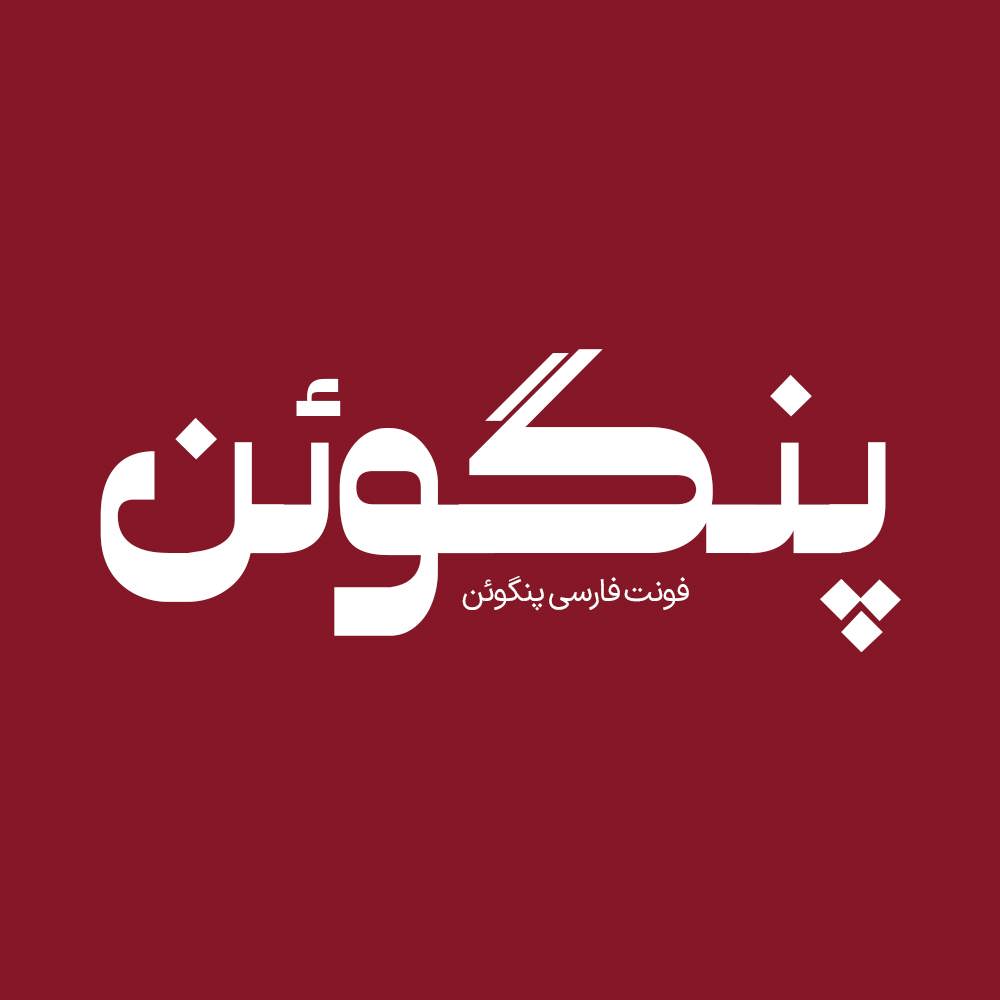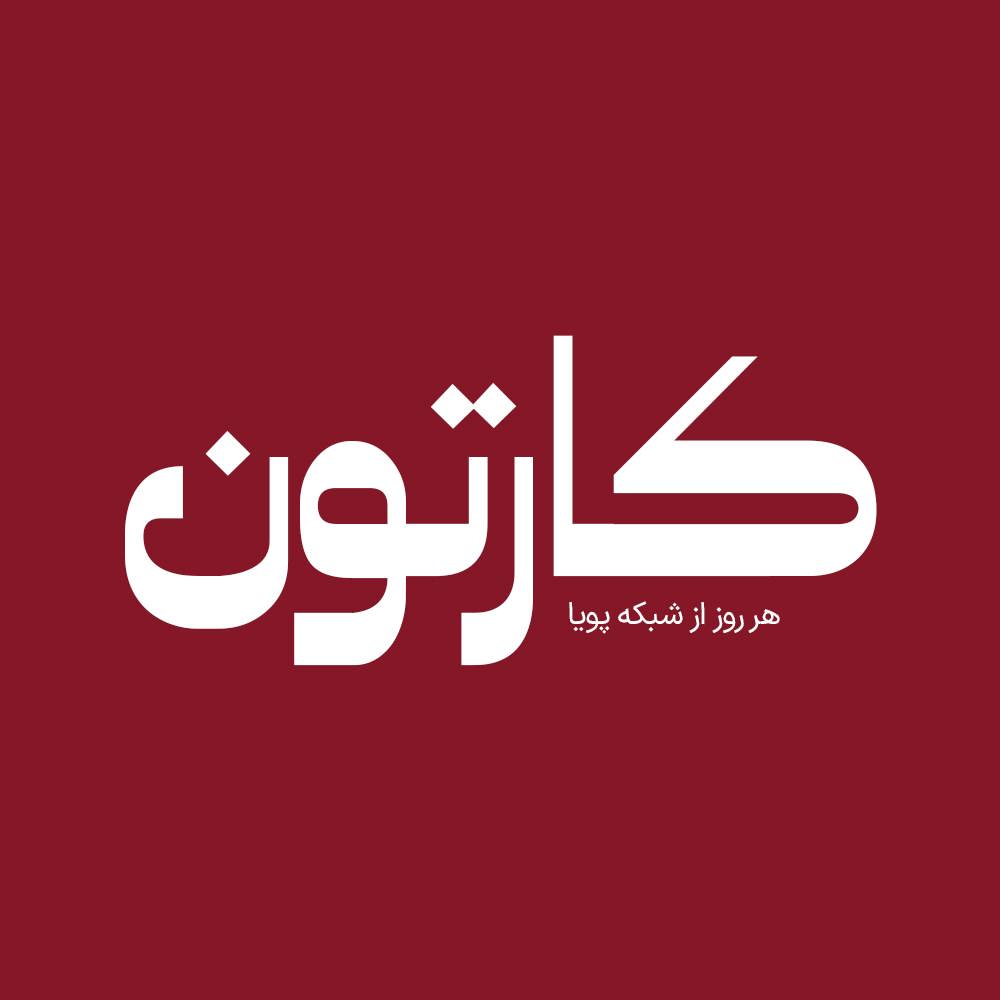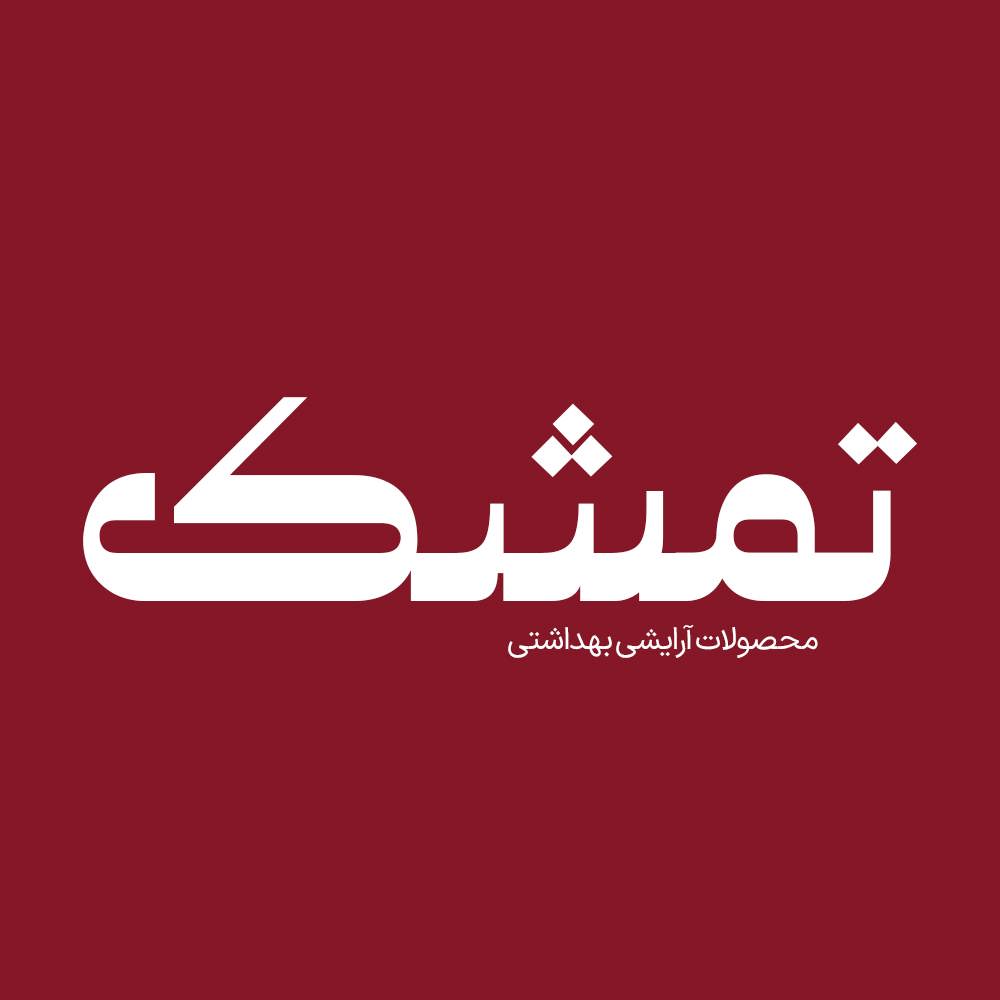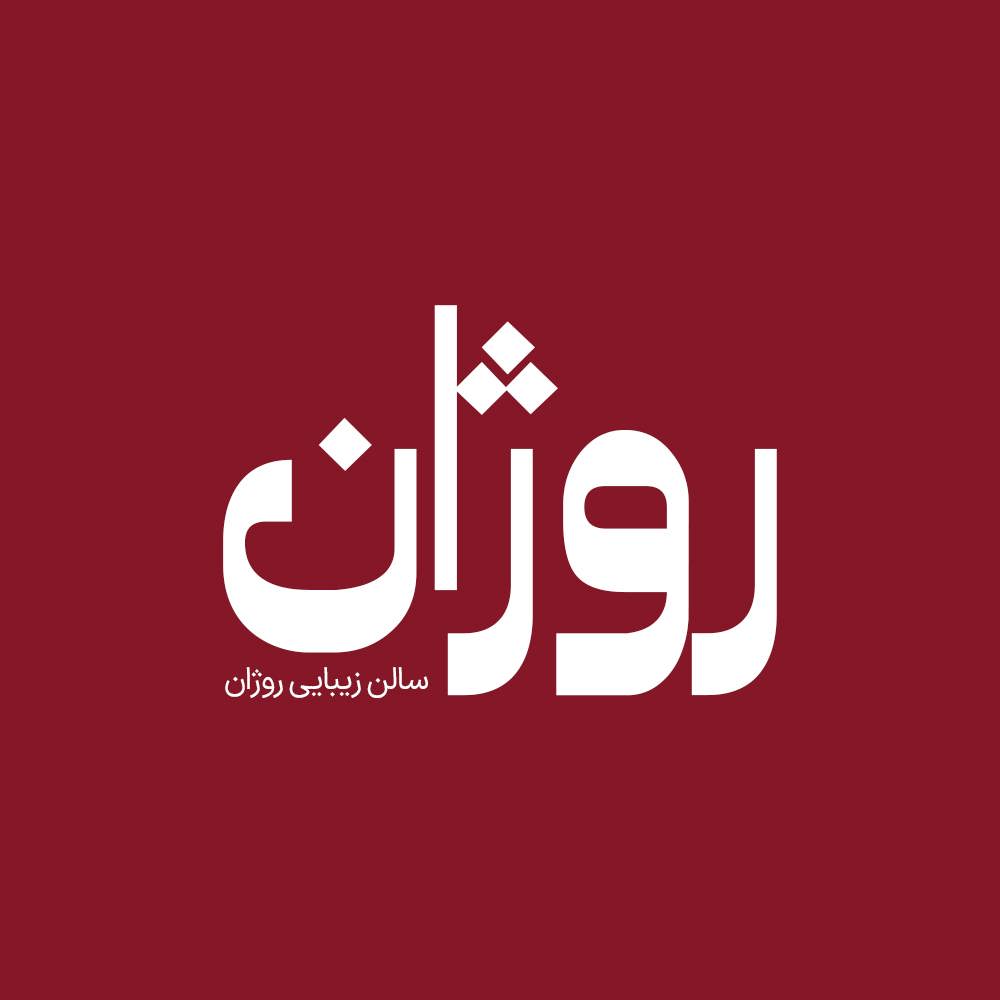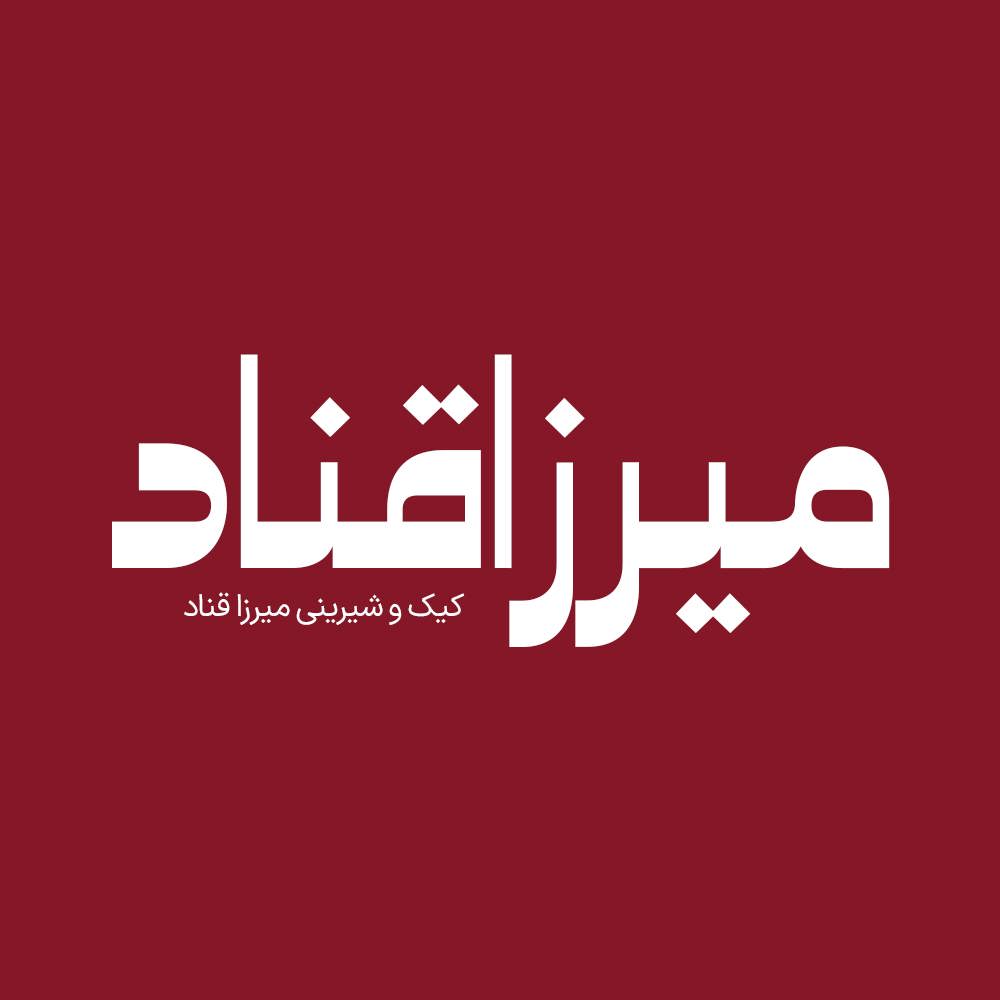
فونت فارسی پنگوئن Penguin Font
فونت فارسی پنگوئن یک فونت تک وزن با کاربرد طراحی لوگوتایپ و طراحی های مختلف همچون کتاب و تولید محتوای متن های کوتاه و عناوین می باشد. فونت پنگوئن با ساختار حروف خود مناسب استفاده در محتوای نوشتاری می باشد. همچنین از این فونت در طراحی تابلوهای چلنیوم هم به دلیل ساختار منحصر به فردش می توانید استفاده کنید.
فونت پنگوئن یک فونت عربی، فارسی سازی و بهینه شده است که برای طراحی انواع امور گرافیکی به خصوص طراحی انواع لوگوتایپ و تایپوگرافی می باشد. از آنجایی که فونت هایی عربی فاقد حروف “گچ پژ” هستند و مشکلاتی در تایپ حروف “ک” و “ی” دارند در فونت پنگوئن حروف “گچ پژ” و همچنین اعداد فارسی و انگلیسی اضافه شده است و بعضی حروف بازطراحی شده اند تا بتوانید تمامی متن فارسی را به وسیله این فونت تایپ کنید. در ادامه برای شما نمونه تایپ های این محصول حرفه ای رو آماده کردیم که میتونید مشاهده کنید.
پیشنمایش و نمونه تایپ های فونت پنگوئن